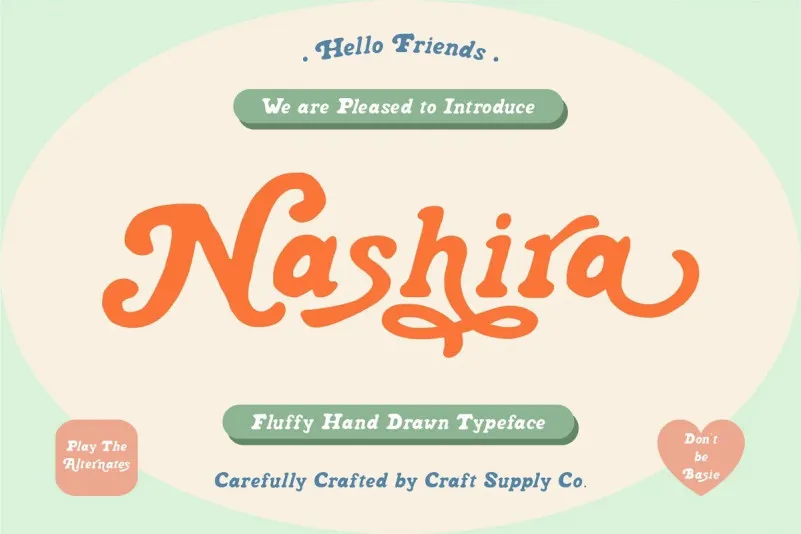
Nashira é uma fonte serif elegante e feminina que traz a sofisticação dos caracteres finais associados à tipografia serifada. Criada pelo Craft Supply Co, ela se destaca com suas ligações sutis e delicadas, adicionando um toque de vida a qualquer projeto gráfico. Imagine sua ideia transformada com Nashira: uma paleta de textos que vai além da simples escrita clássica para algo mais sofisticado e envolvente. Com Nashira, você pode fazer seu trabalho brilhar ainda mais, dando-lhe um toque único e atraente capaz de destacar qualquer projeto em sua categoria. E com suas ligações encorpadas que remetem a uma escrita à mão livre, a fonte traz aos seus projetos uma personalidade única e envolvente. O design cuidadoso da Nashira faz dela uma escolha perfeita para quem procura um equilíbrio entre elegância e delicadeza em suas produções.